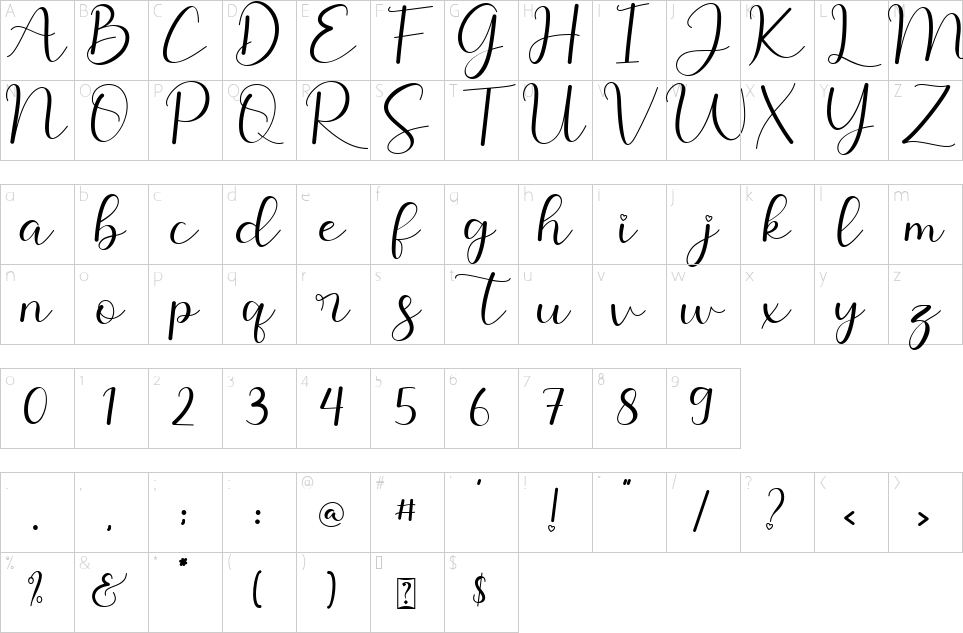
Descubra a Alessea, uma fonte exclusivamente gratuita que se destaca por sua elegância moderna. Desenvolvida pela AEN Creative Studio, esta fonte oferece uma experiência visual única e fluida em ambientes Windows e Mac. Seu design minimalista e sofisticado combina perfeitamente em diversos projetos de design, desde textos em sites pessoais até gráficos de marketing. Com uma simplicidade que chama a atenção, a Alessea é uma escolha ideal para designers que buscam uma fonte moderna e versátil sem precisar gastar. Com apenas 3. 390 downloads, é evidente que os designers valorizam a Alessea. Esta fonte é perfeita para quem está em busca de uma opção de fonte gratuita que possa transformar seus projetos de design em algo ainda mais notável.